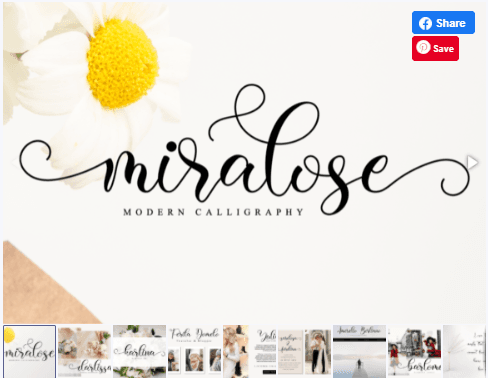
Miralose Font
Miralose - очаровательный рукописный шрифт. Этот универсальный скриптовый шрифт имеет широкий спектр применения, от поздравительных открыток до заголовков, и гарантированно добавит романтики вашему следующему проекту. Этот шрифт имеет кодировку PUA, что означает, что вы можете легко получить доступ ко всем красивым глифам и росчеркам!